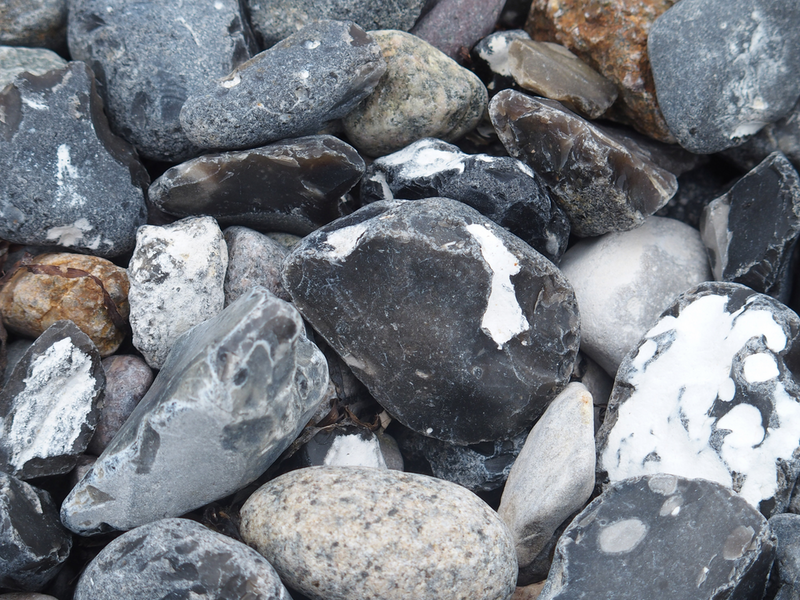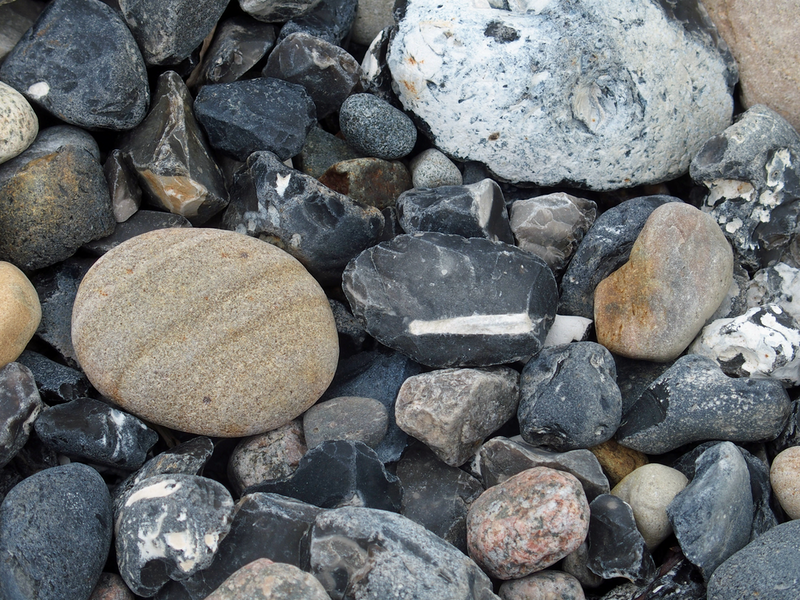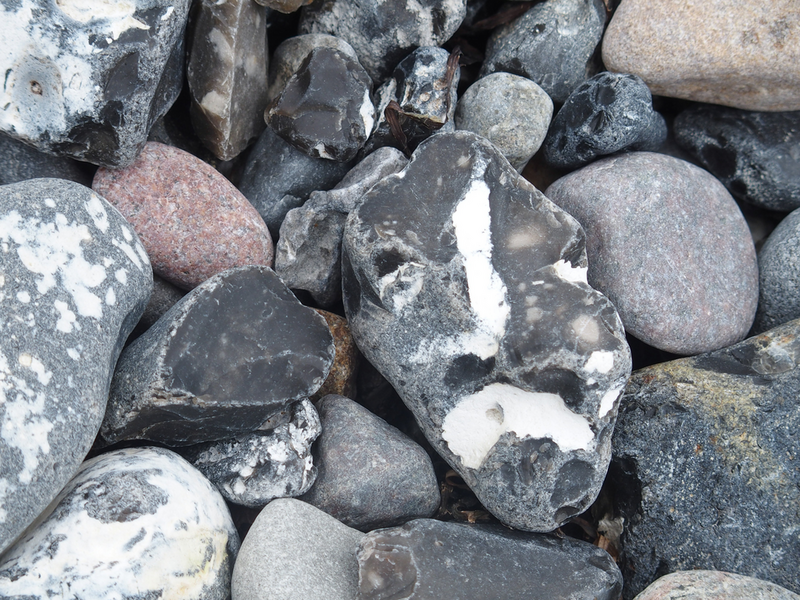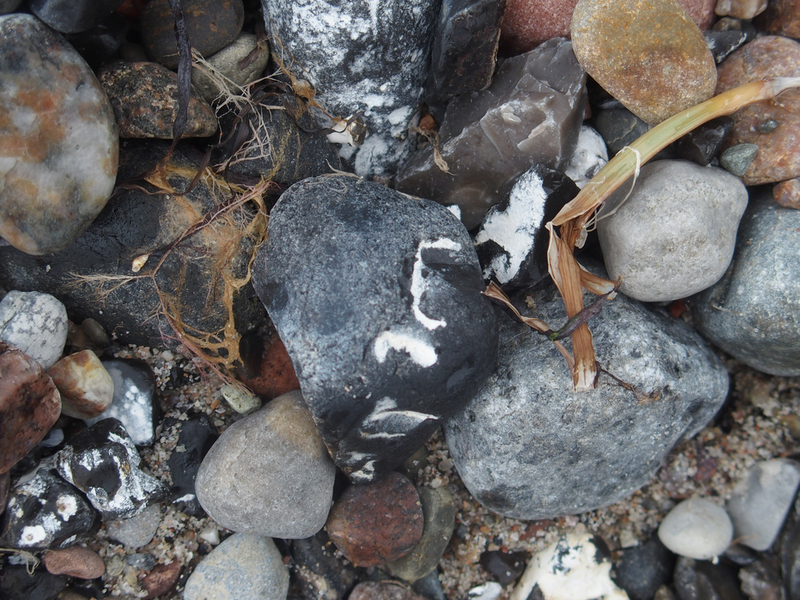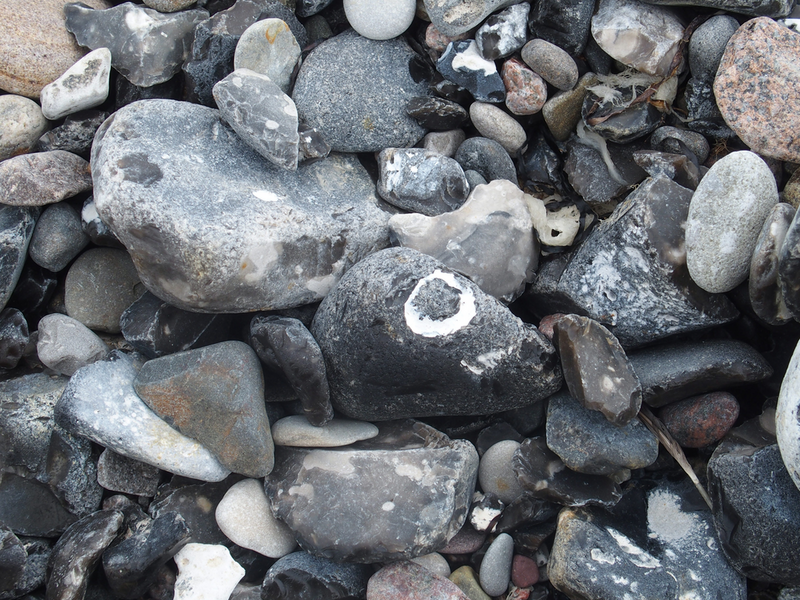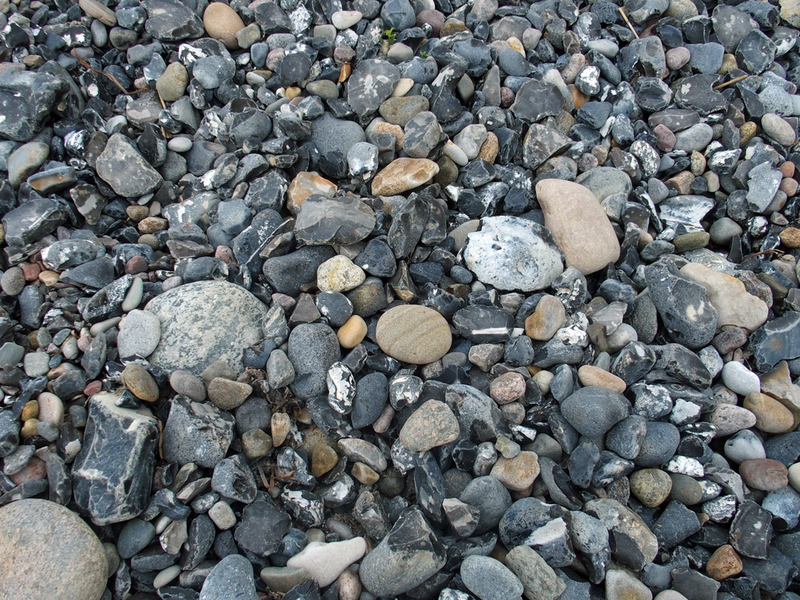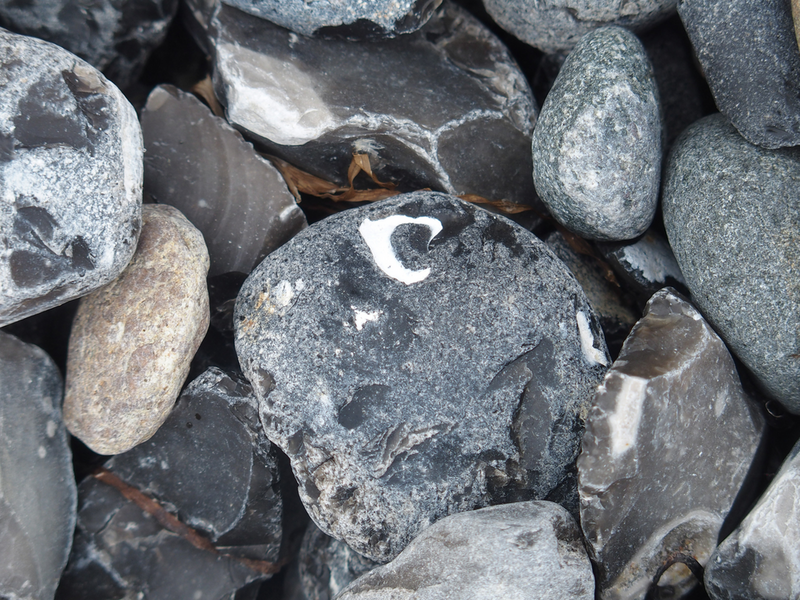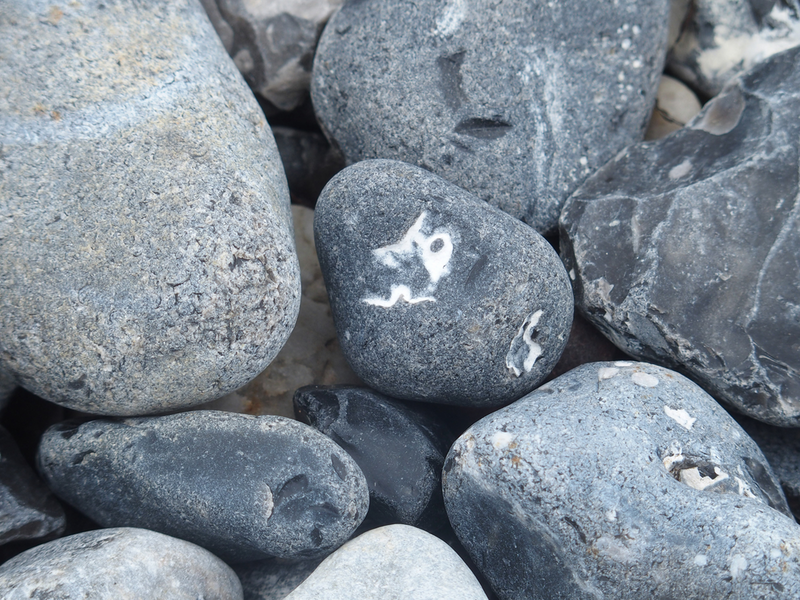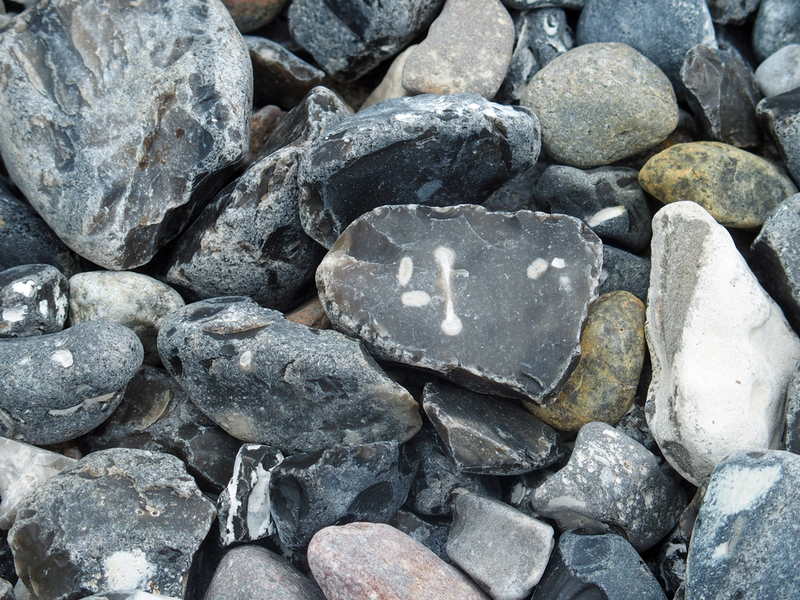
Ostseetypografie Teil 8 - Stein-Typografie Teil 4
Wieder einmal war ich zu einem Kurzurlaub an der Ostsee. Ich fahre meist auf die Insel Rügen.
Dort gibt es an vielen Orten schöne Feuersteine. Die beste Stelle für mich, um Steine mit schönen Zeichnungen Buchstaben oder Symbolen zu finden, ist in Bug. Bug liegt in der Nähe von Dranske auf der Halbinsel Wittow und ist eine schmale Landzunge am Ende der Halbinsel. Direkt gegenüber hat man den Blick auf die Insel Hiddensee mit ihrem Leuchturm auf dem Dornbusch.
Man muss nur richtig hinsehen, dann findet man die besonderen Feuersteine, auf denen das Meer, der Wind, Muschelkalk und ganz wichtig die Zeit Buchstaben, Symbole oder ganz mystische Zeichen gemalt hat. Zugegeben gehört auch manchmal etwas Phantasie und Vorstellungskraft dazu.
Zuerst mal ein Beispiel, wie man aus gefühlt hunderten von Steinen den „Einen“ mit z.B. einem langen Bindestrich – einem Geviertstrich oder Gedankenstrich findet.
Hier die Ausbeute meiner Feuersteine mit Buchstaben und Zeichen von diesem Kurzurlaub.